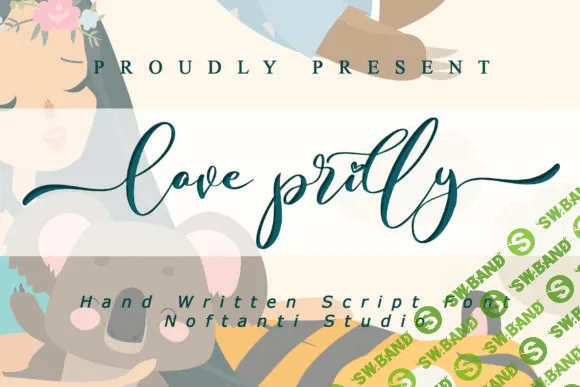
Название: Love Prilly Font
Любовь Прилли - это изысканный, круглый и скорописный рукописный шрифт.
Он имеет красивые и хорошо сбалансированные символы и, как результат, соответствует широкому кругу дизайнерских решений.